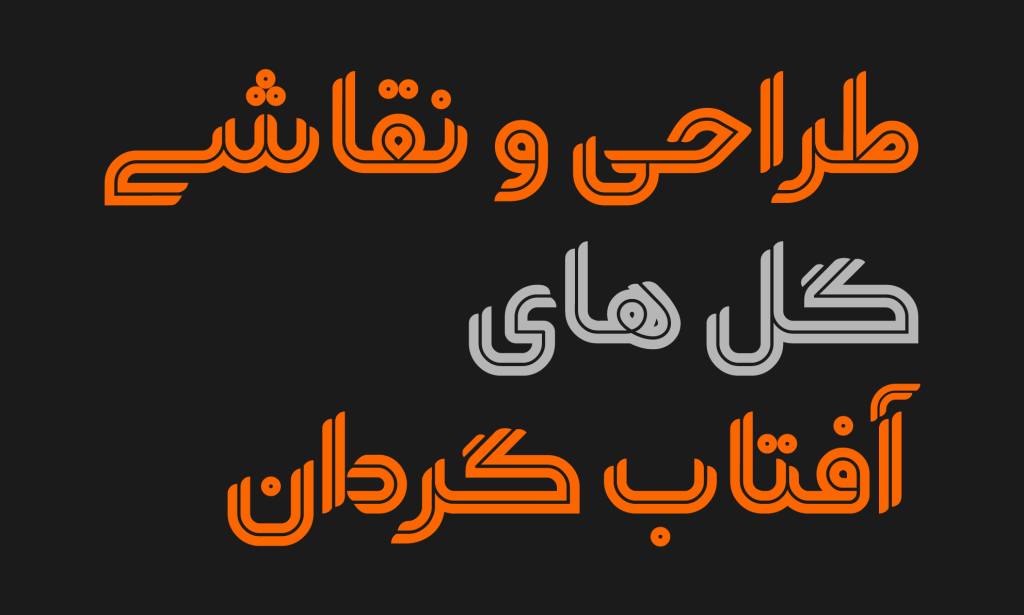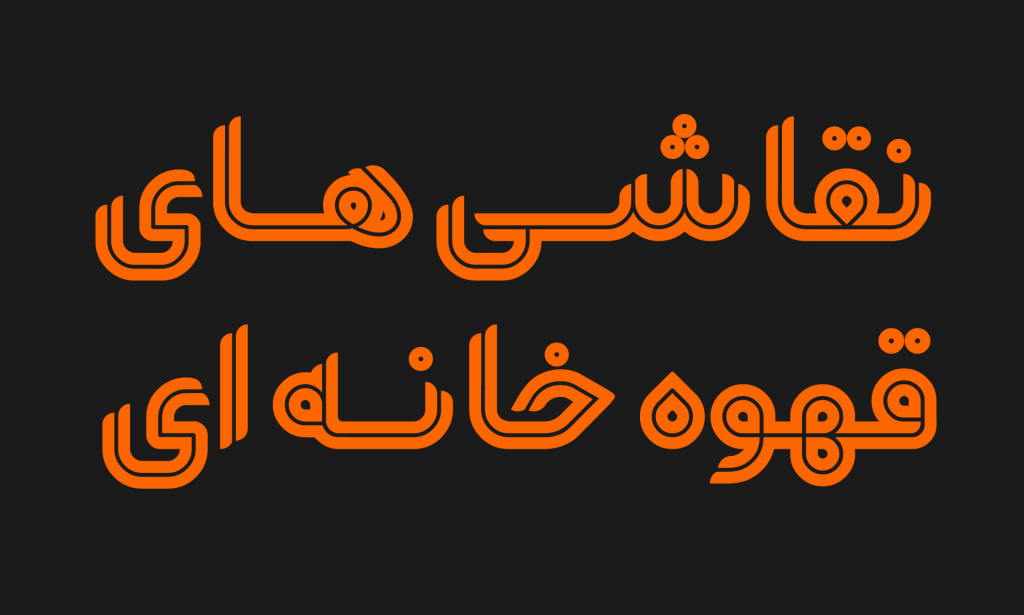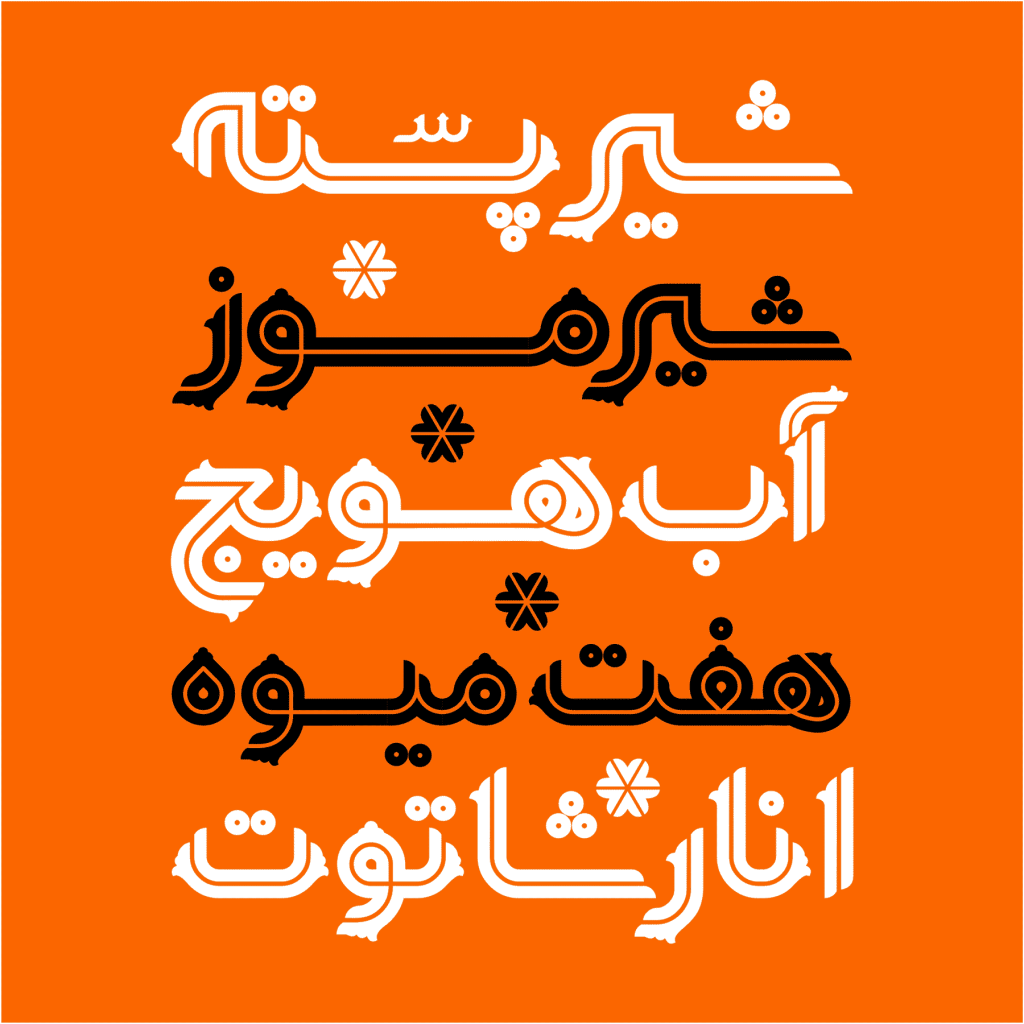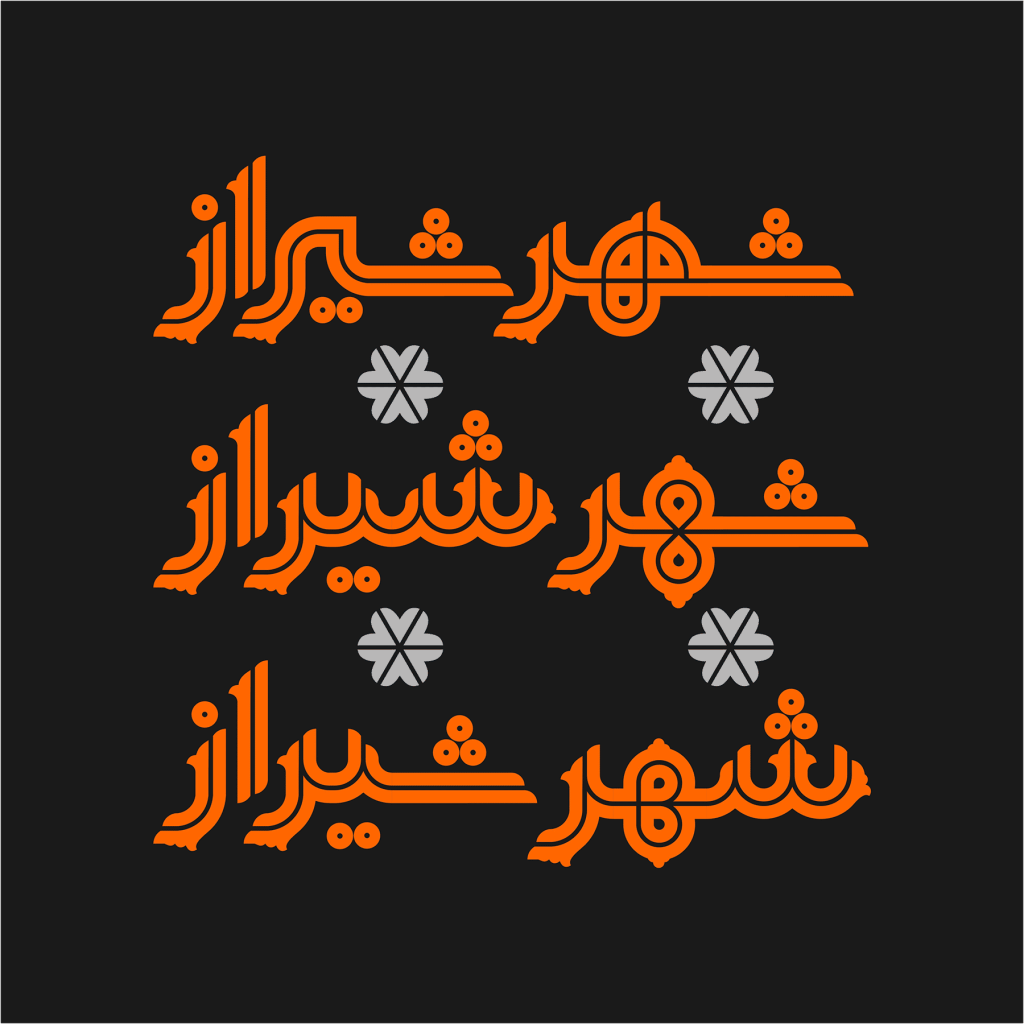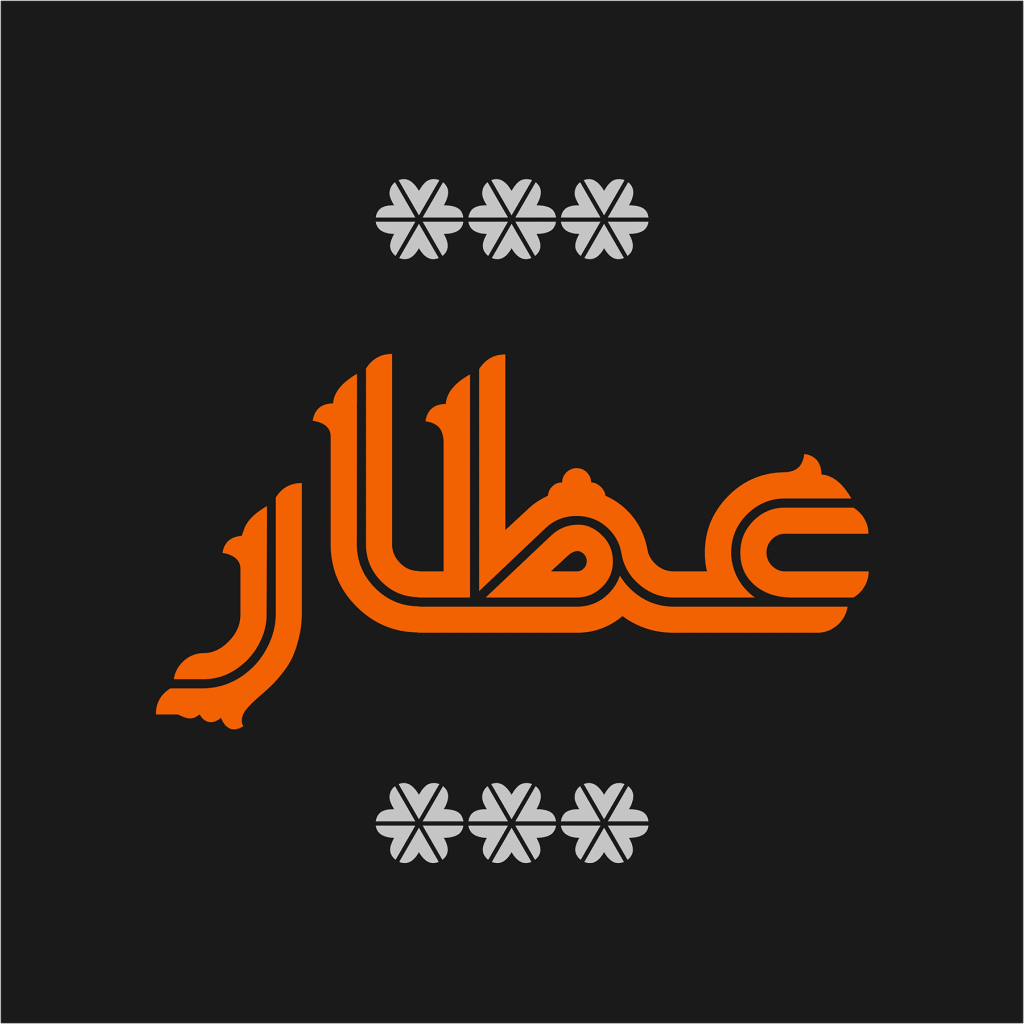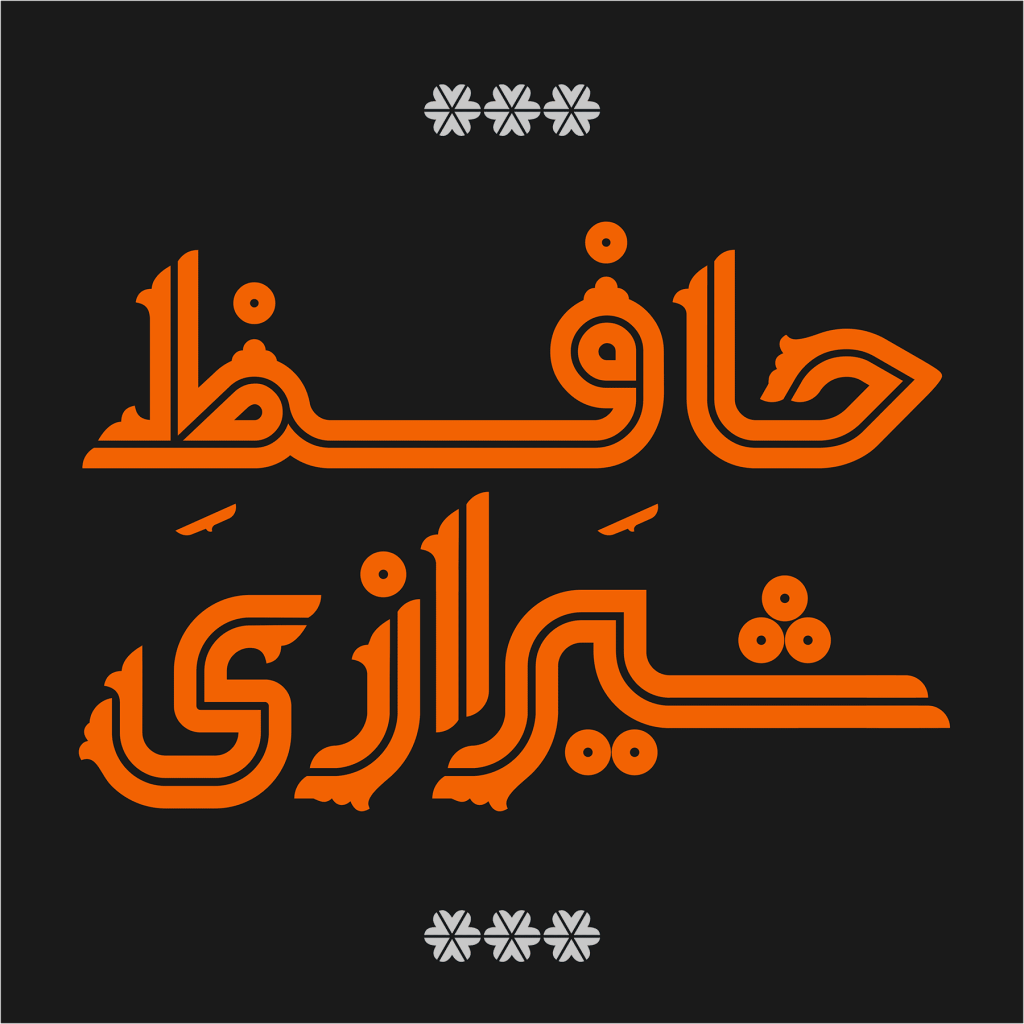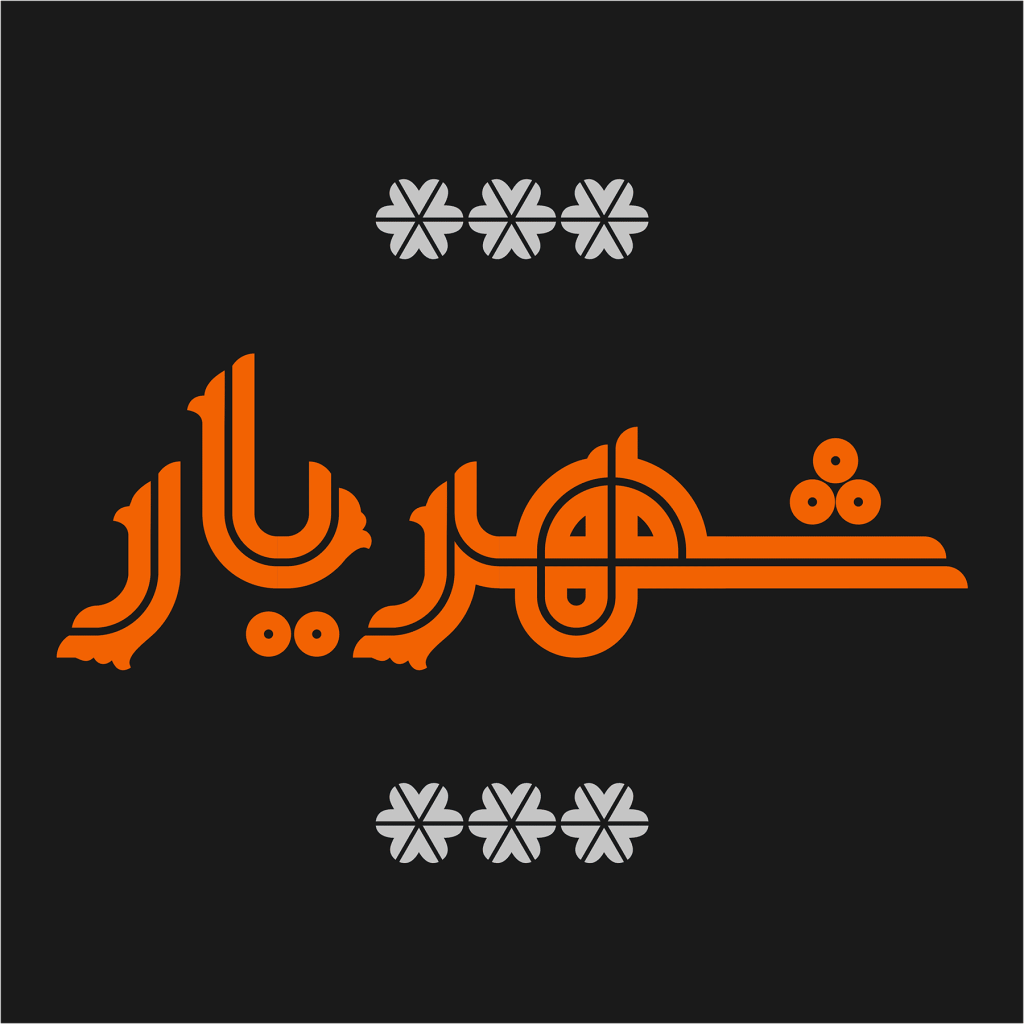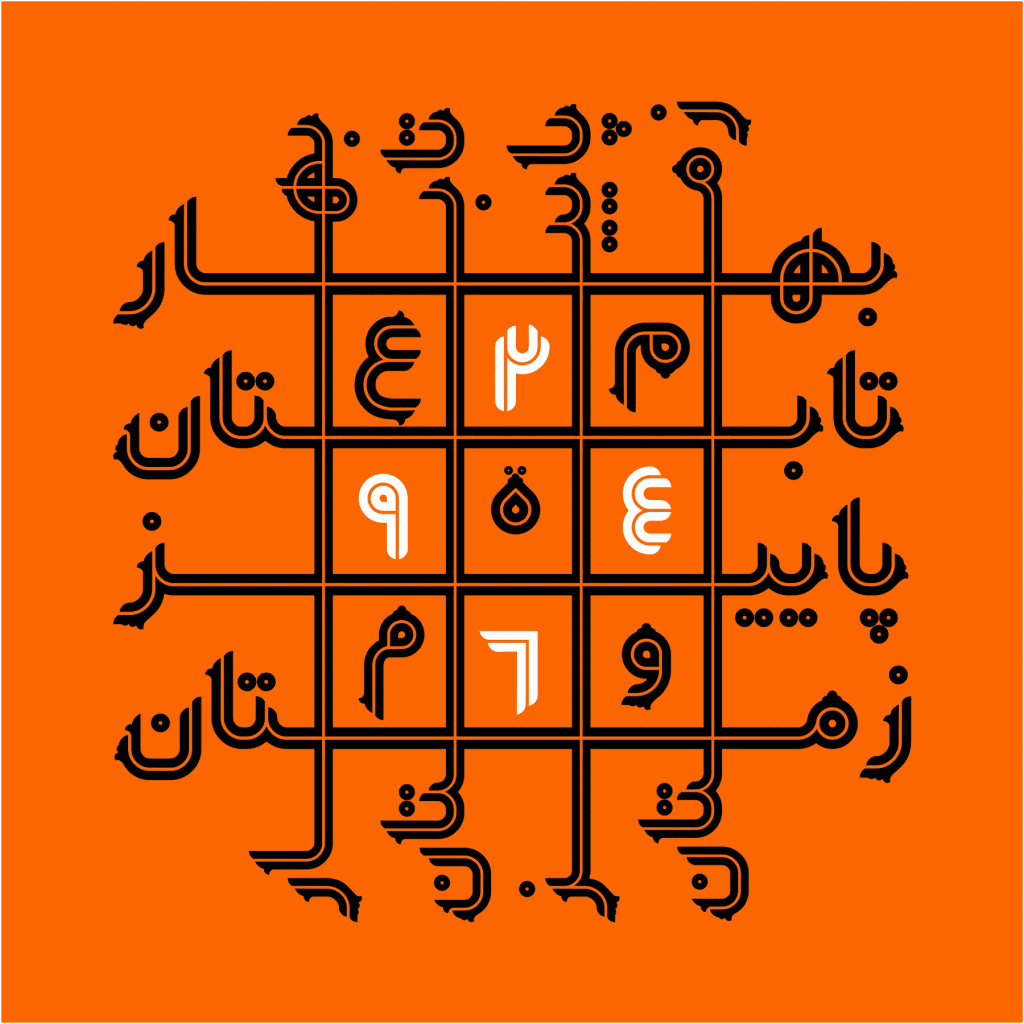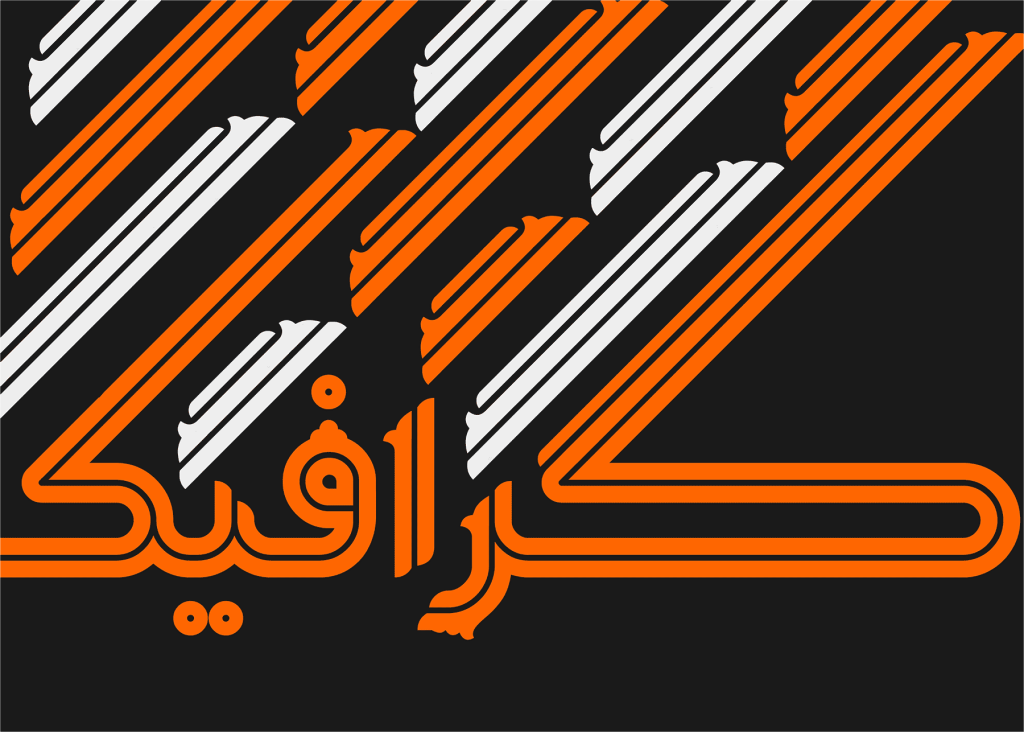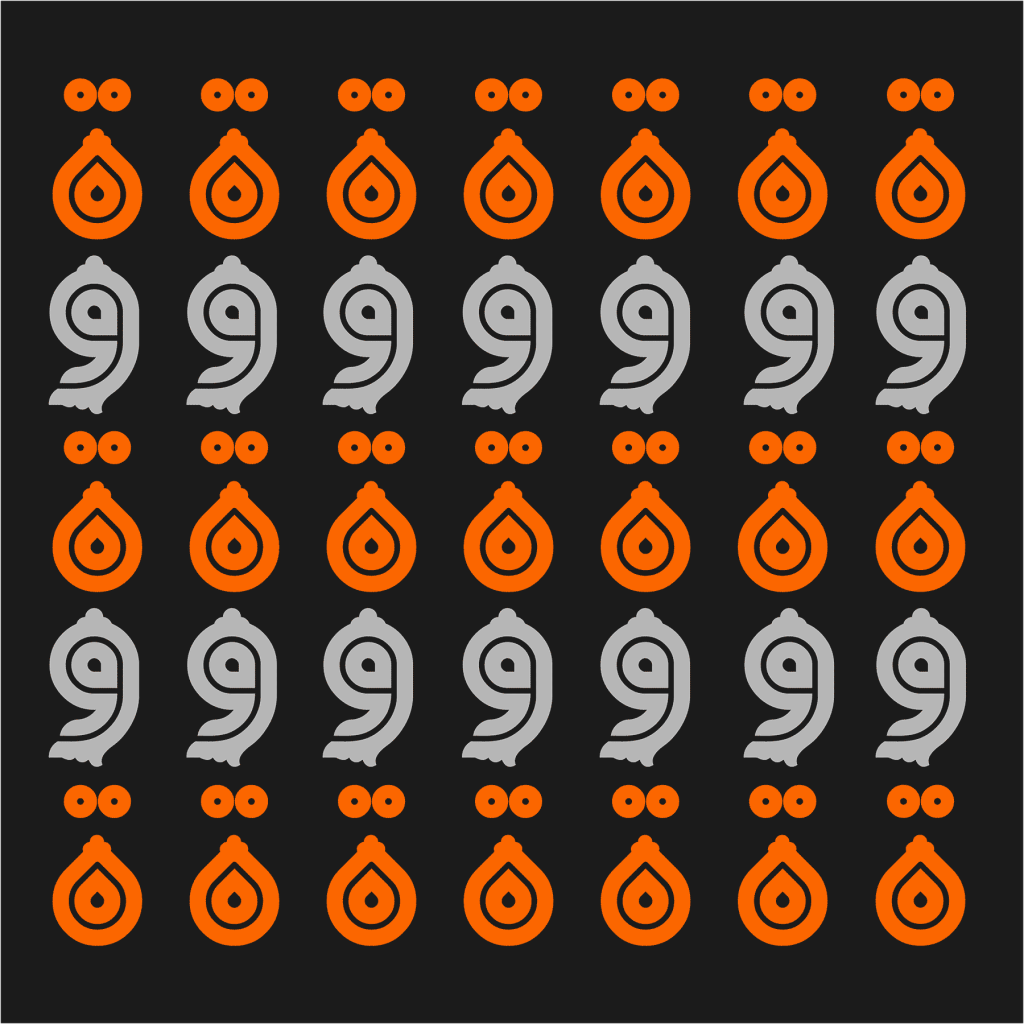
فونت یکتا قلمی از خانواده هندسی دارای ویژگی نمایشی بالا و منحصر به فرد برای تبلیغات ادبی هنری و مذهبی به دلیل داشتن نقوش اسلیمی است این قلم به همت وحید یعقوب لو طذاحی شده است.
فونت یکتا قلمی هندسی با نقوش اسلیمی
فونت یکتا تایپ فیسی هندسی با قدرت نمایشی و تاثیر گذاری بسیار به دلیل ویژگی تزئینی فرم های آن می باشد. یکتا حس و حال ایرانی دارد . تزئینات و ظرافت های طراحی درآن ، یکتا را همانند نام آن به تایپ فیسی خاص و منحصر به فرد مبدل ساخته است. چرا که کمتر قلمی نزدیک و همانند به آن یافت می شود که تا این اندازه دارای ظرافت های تزئینی در درون فرم های طراحی خود باشد.
فونت دلنیا از نقطه نظر هم خانوادگی و تزئینی بودن حروف و ترکیبات بسیار شبیه به قلم یکتا است. دلنیا با هدف ایجاد مکث و تمرکز خواننده بر محتوا طراحی شده است، بطوری که با صرف زمان بیشتر اطلاعات در ذهن مخاطبان ماندگار شود
جنس تزئینات و تمرکز بر طراحی فرم های حروف، ترکیبات و مفردات قلم یکتا الهام گرفته از نقوش اسلیمی است. که ریشه در فرهنگ اصیل ایرانی دارد و ارتباط نزدیکی با مخاطب خود برقرار می کند. ساختار و شاکله اصلی فرم های طراحی در این تایپ متشکل از خطوط صاف و منحنی های نرم و منعطف است . همین امر حس صمیمت و یکدلی را به مخاطب انتقال می دهد و بر تاثیر گذاری بیشتر آن می افزاید.
یکتا دارای شخصیتی اصیل و با اصالت است که ریشه خود را از فرهنگ غنی ایرانی به ازث می برد. اما در عین حال با اصلاحات و تغییراتی که در آن صورت پذیرفته بیگانه با محیط های امروزی و مدرن نیست. کاربرد استفاده از یکتا از صنعت نشر و چاپ گرفته تا دنیای وب و دیجیتال گسترده و وسیع است.
شما عزیزان می توانید با استفاده از نرم افزار های طراحی برای خلق انواع متون و عناوین تبلیغاتی و جذاب در حوزه های مختلف هنری ادبی مذهبی از این قلم منحصز به فرد و خاص استفاده کنید. این قلم ماحصل تلاش چند ساله طراحان مطرح تایپوگرافی فارسی (وحید یعقوبلو و امین عابدی) بوده است و دارای 2 استایل مختلف می باشد.